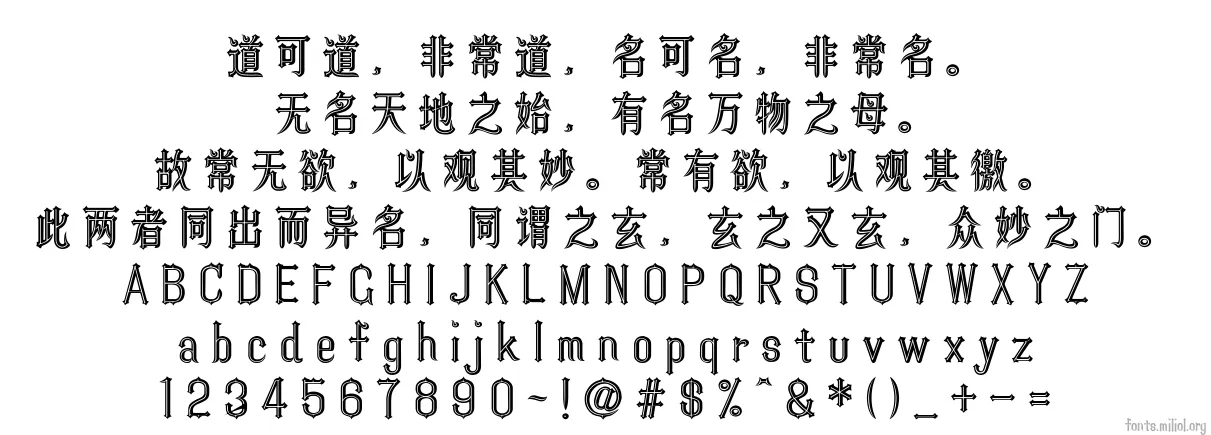
**方正青铜体简体:传统与现代交融的字体艺术**
方正青铜体简体(FZQingTongTiS-R-GB)是一款兼具古典韵味与现代设计感的字体,其灵感源自青铜器铭文的厚重与端庄。字体线条刚劲有力,笔画转折处保留了青铜纹饰的雕琢感,同时通过简化的结构适应现代排版需求,展现出传统与创新的完美结合。
这款字体适用于文化宣传、历史主题设计或品牌标识等场景,能为作品增添独特的文化底蕴。其标准化的GB编码(FZQTTJW--GB1-0)确保了广泛的兼容性,适合印刷与数字媒体使用。方正青铜体简体的设计既是对中华文明的致敬,也为现代视觉表达提供了新的可能性,是设计师诠释东方美学的优质选择。